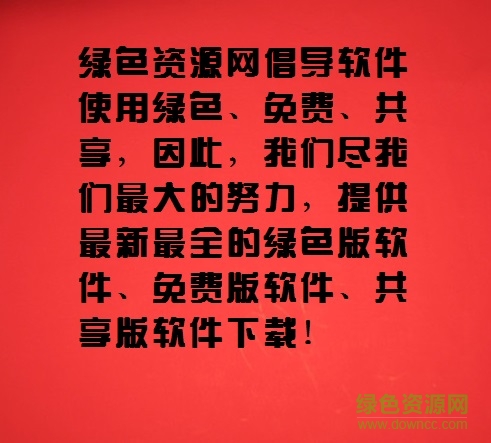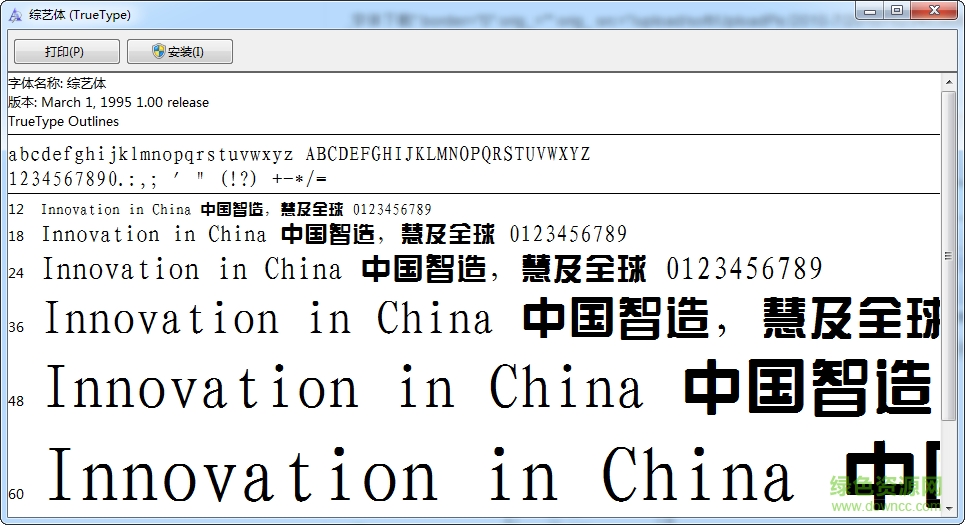
四通利方綜藝體字體其字體形體方正,筆畫平直,小字運(yùn)筆圓潤(rùn)、娟秀、挺拔、整齊、大字雄壯、厚重,是一款極其的講究的字體,本次我們將該字體的文件下載地址推薦給大家,歡迎大家的使用。
四通利方綜藝體字體端秀清新,筆畫方圓兼?zhèn)?,曲線舒展,橫畫首尾呼應(yīng),溫潤(rùn)秀美,整體風(fēng)格不燥不潤(rùn)、張弛有度,有極強(qiáng)的視覺(jué)表現(xiàn)力。此款字體適用于海報(bào)設(shè)計(jì)、報(bào)刊雜志標(biāo)題、書籍封面設(shè)計(jì)等應(yīng)用。